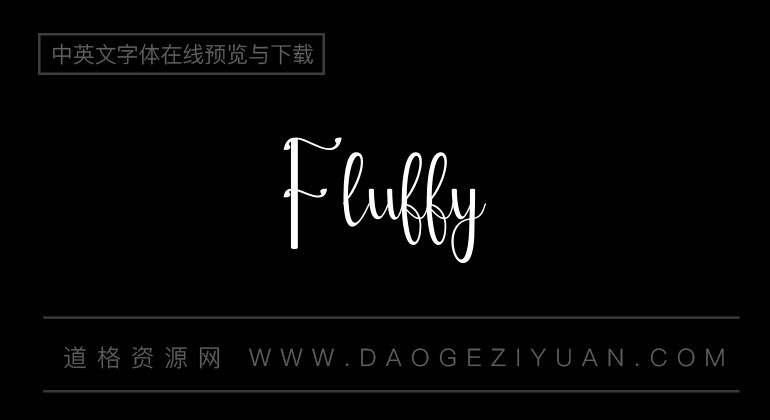
Fluffy 字体是一种非常可爱、圆润、柔和的字体。它的设计灵感源自于毛绒玩具,因此被称为 Fluffy(毛茸茸的)字体。这种字体通常使用粉色、浅蓝色、紫色等柔和的颜色,给人以温暖、可亲的感觉。Fluffy 字体适合用于制作卡通、儿童教育、婚庆、情人节等温馨、浪漫的场合。内容介绍
Fluffy是一款非常不错的手写艺术字体,具有很好的视觉感,适合于文化类的宣传设计、商业类品牌的广告和产品包装设计以及个性化文字排版等较多场景。